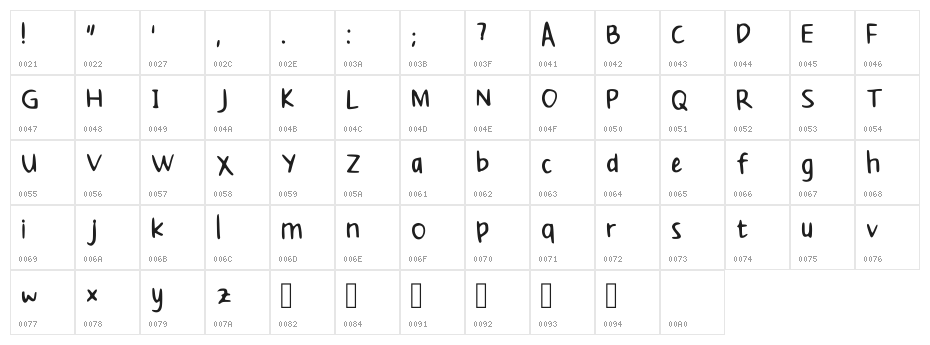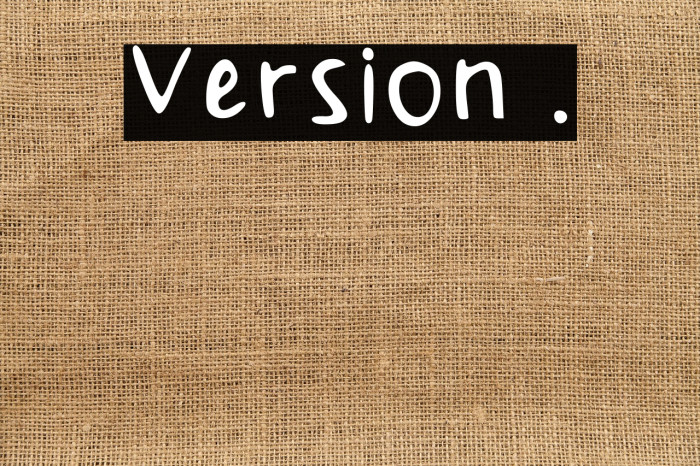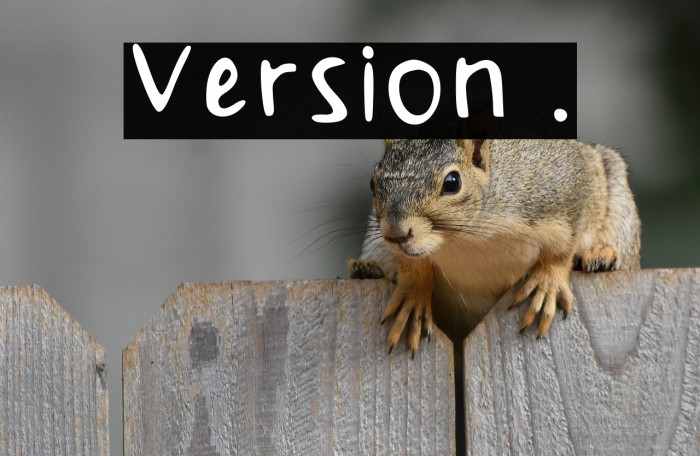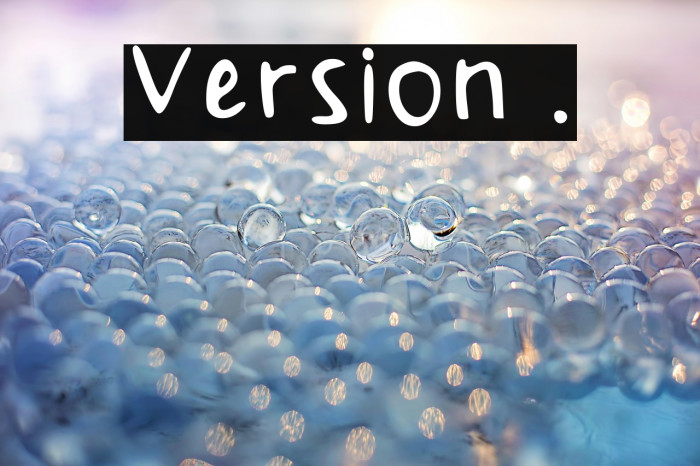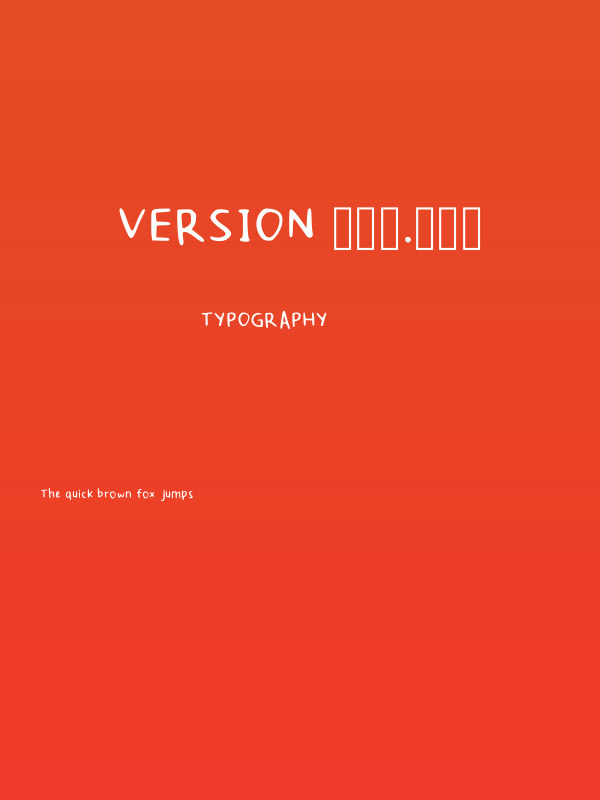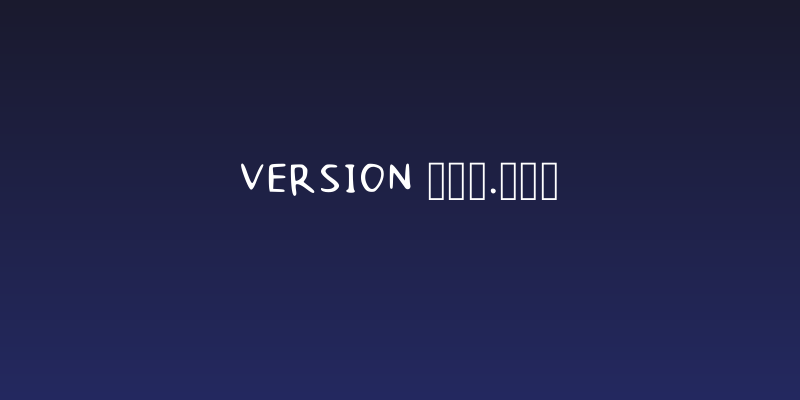
Version 001.002 Font
✎ Regular
| Gesamtstil | Casual, Playful |
| Anwendungsfall | Headlines, Informal text, Personal projects |
| Vorgeschlagene Projekte | Ideal for children's books, greeting cards, personal blogs, and informal branding. |